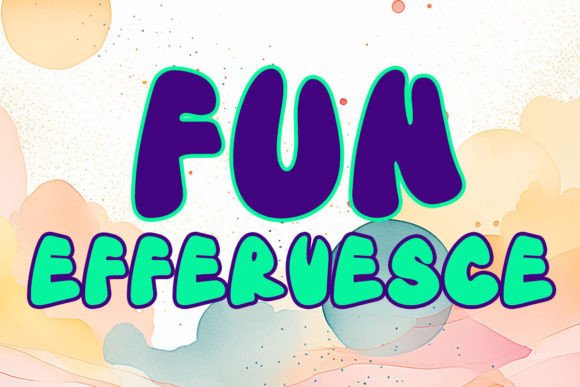
Effervesce Fun
Mencari elemen reka bentuk yang sesuai boleh menjadi mencabar, tetapi Effervesce Fun menawarkan koleksi luar biasa yang menaik taraf karya anda serta-merta.
Sama ada anda mencipta produk POD (Print on Demand), jemputan perkahwinan atau grafik media sosial, Effervesce Fun amat bersesuaian.